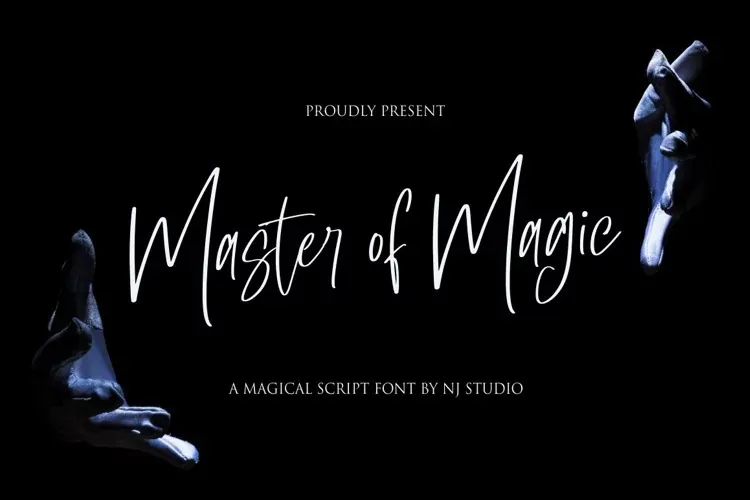
Esta é uma fonte para script criada a partir do trabalho meticuloso de um designer chamado NJ Studio. Ela se destaca pela sua escrita manuscrita com traços relaxados e eternos, perfeita tanto para projetos profissionais quanto pessoais. O texto ligaturado que ela contém irá levá-la a outro nível! Este é um recurso visual único que não apenas adorna seus documentos, mas também os torna mais intrigantes e inovadores. Ideal tanto para criações empresariais quanto para design de arte pessoal, essa fonte doador de estilo será uma escolha inteligente para qualquer designer que procura algo diferente e sofisticado. Descubra a magia única desta fonte “Master of Magic” em sua próxima projeto criativo.